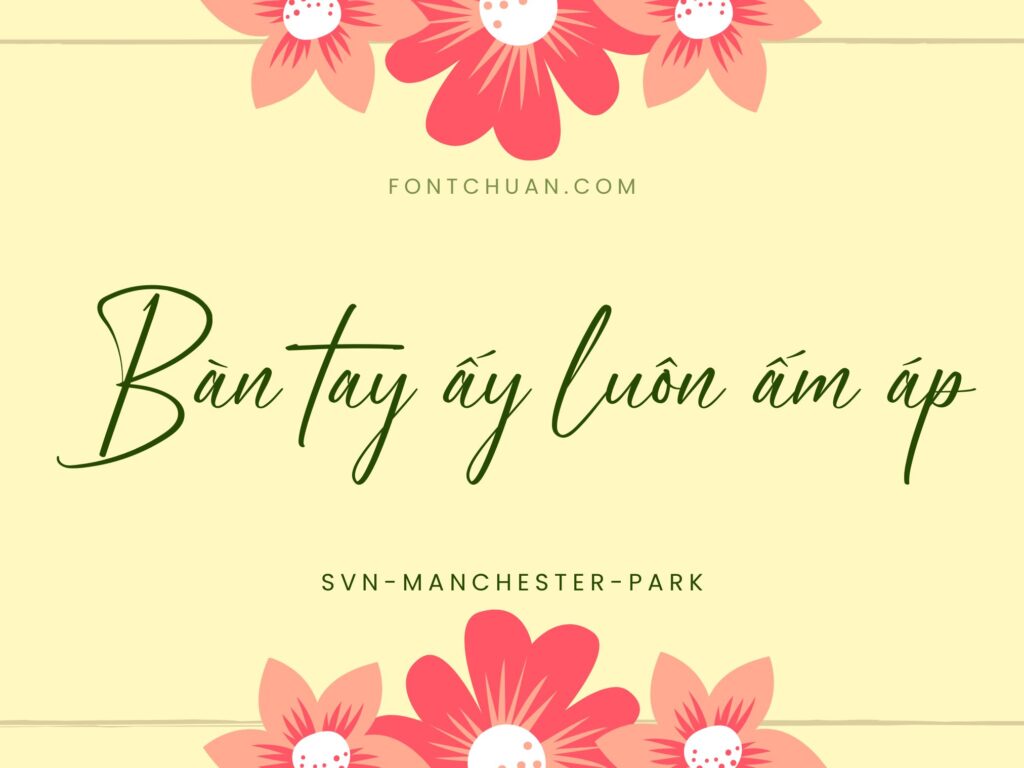
Font SVN Manchester Park Việt Hóa
Tác giả Font: Widiyanti & Sarah Suci P
Font SVN Manchester Park là phiên bản Việt hóa của kiểu chữ Manchester Park, được thực hiện bởi STYLEno.1 Fonts. Manchester Park là một kiểu chữ viết tay mang phong cách Font chữ thư pháp, được thiết kế bởi Widiyanti & Sarah Suci P và phát hành bởi Noahtype. Font này nổi bật với các đường nét uyển chuyển và thanh lịch, tạo cảm giác sang trọng và tinh tế. Manchester Park bao gồm đầy đủ các ký tự chữ hoa, chữ thường, chữ số và dấu câu, hỗ trợ đa ngôn ngữ. Ngoài ra, font còn được mã hóa PUA, cho phép truy cập dễ dàng vào các glyphs và ligatures đặc biệt. Font này phù hợp cho nhiều mục đích sử dụng như thiết kế thiệp mời, logo, tiêu đề, bao bì sản phẩm và các ấn phẩm truyền thông.
SVN Manchester Park lý tưởng cho các dự án thiết kế yêu cầu sự thanh lịch và tinh tế, như thiết kế thiệp mời, logo thương hiệu và các ấn phẩm truyền thông. Các ngành nghề như thiệp cưới, giáo dục và ẩm thực có thể tận dụng font này để tạo điểm nhấn trong thiết kế. Ngoài ra, font cũng thích hợp cho các sự kiện như Valentine, Sinh nhật, Tết và các lễ hội khác.